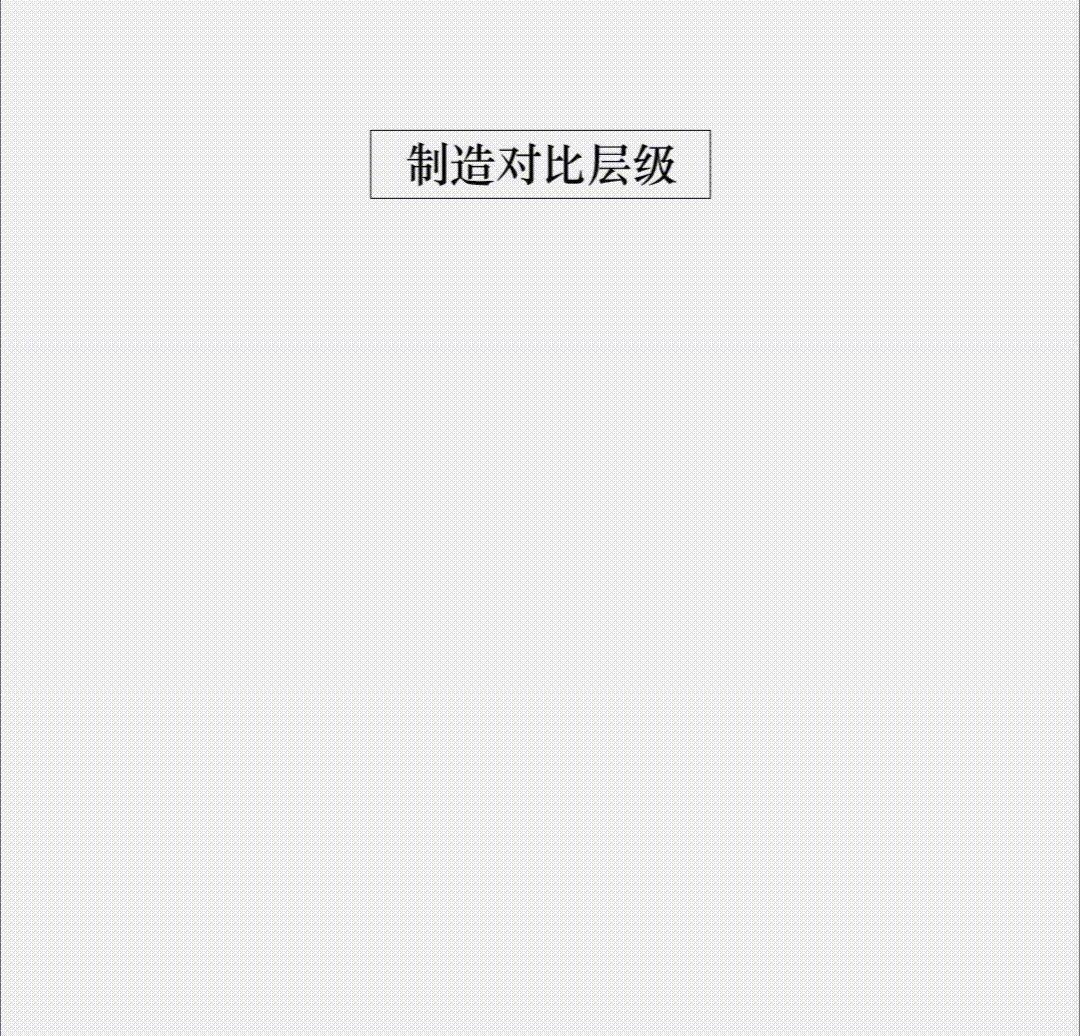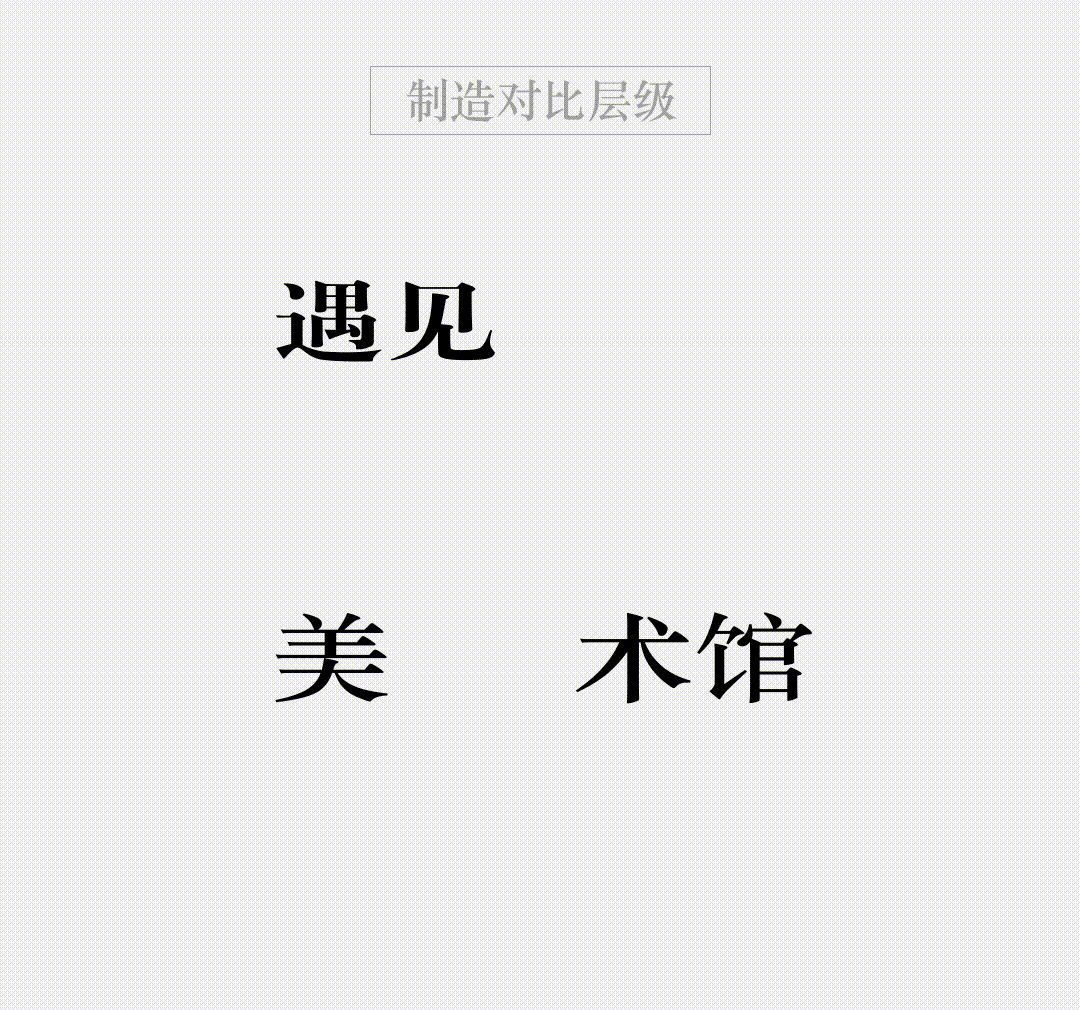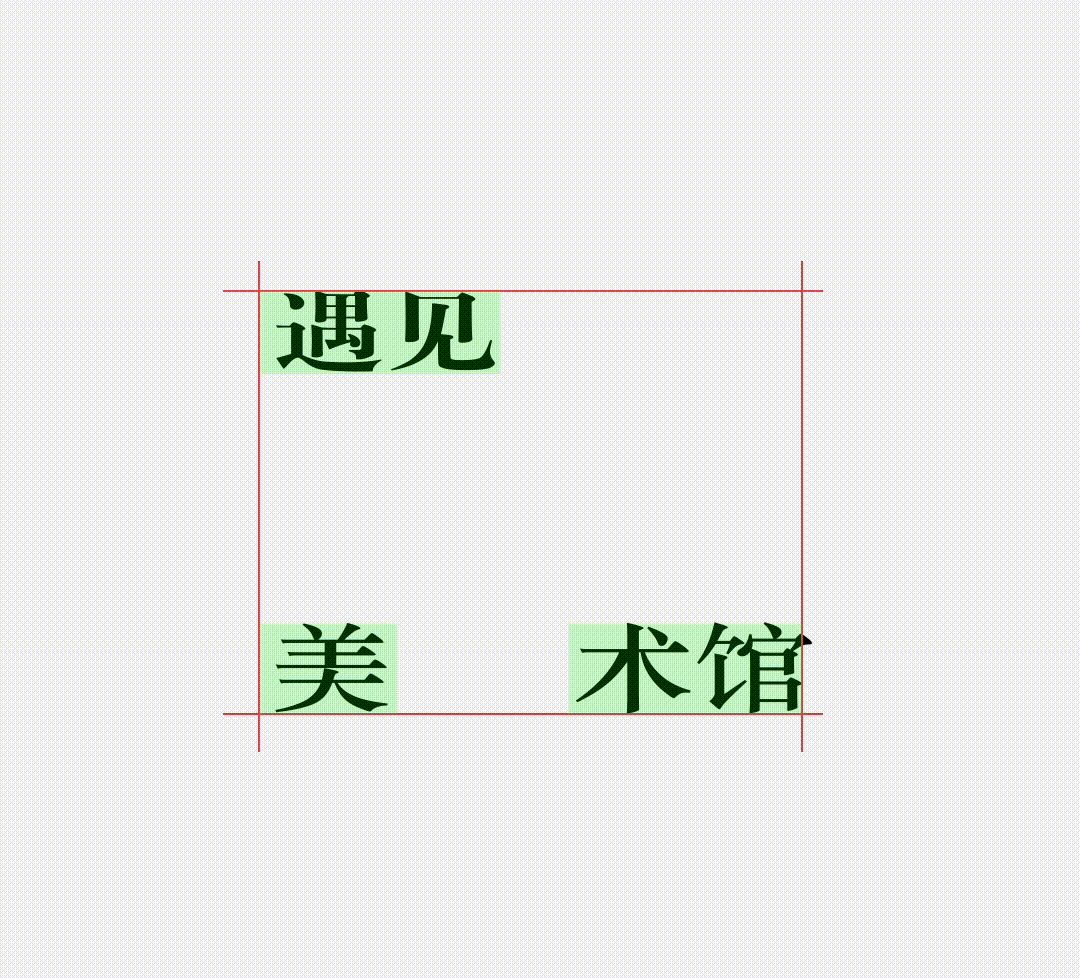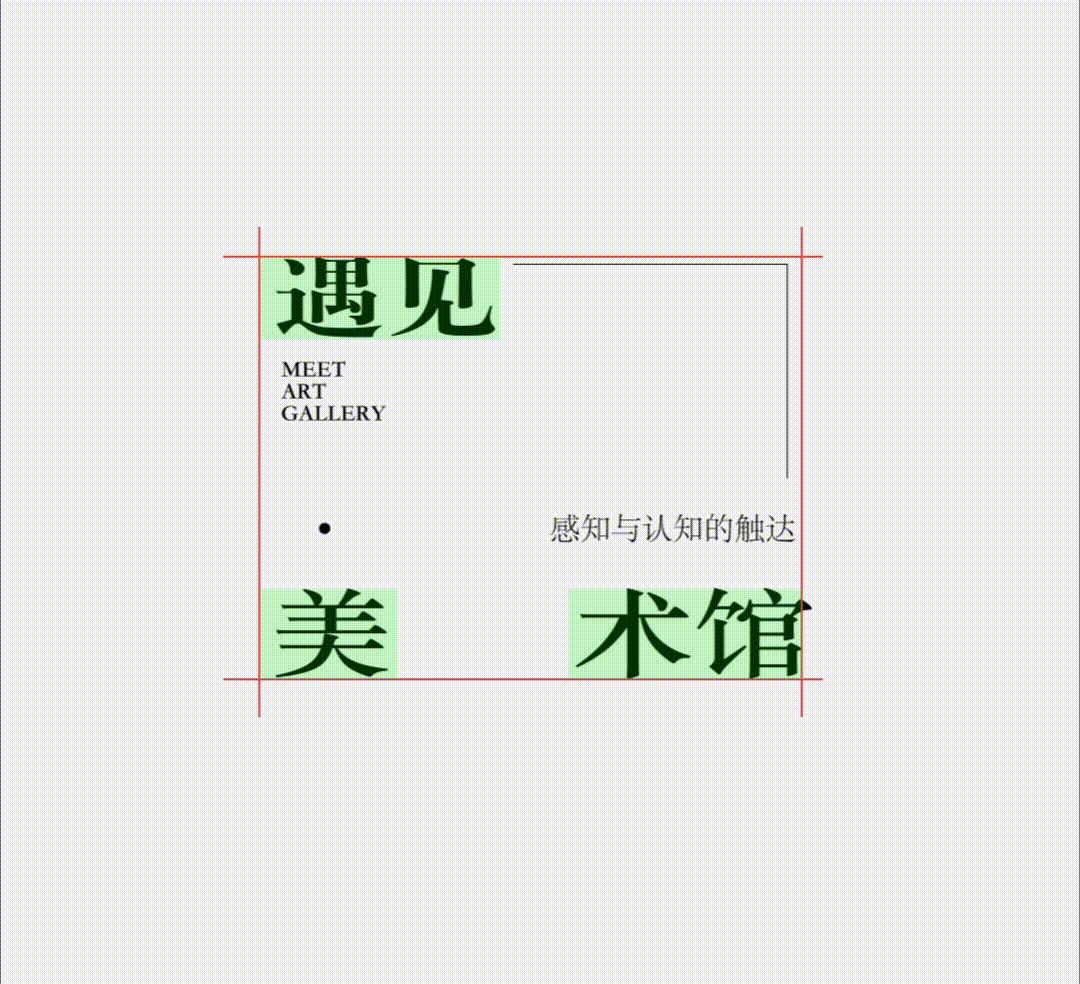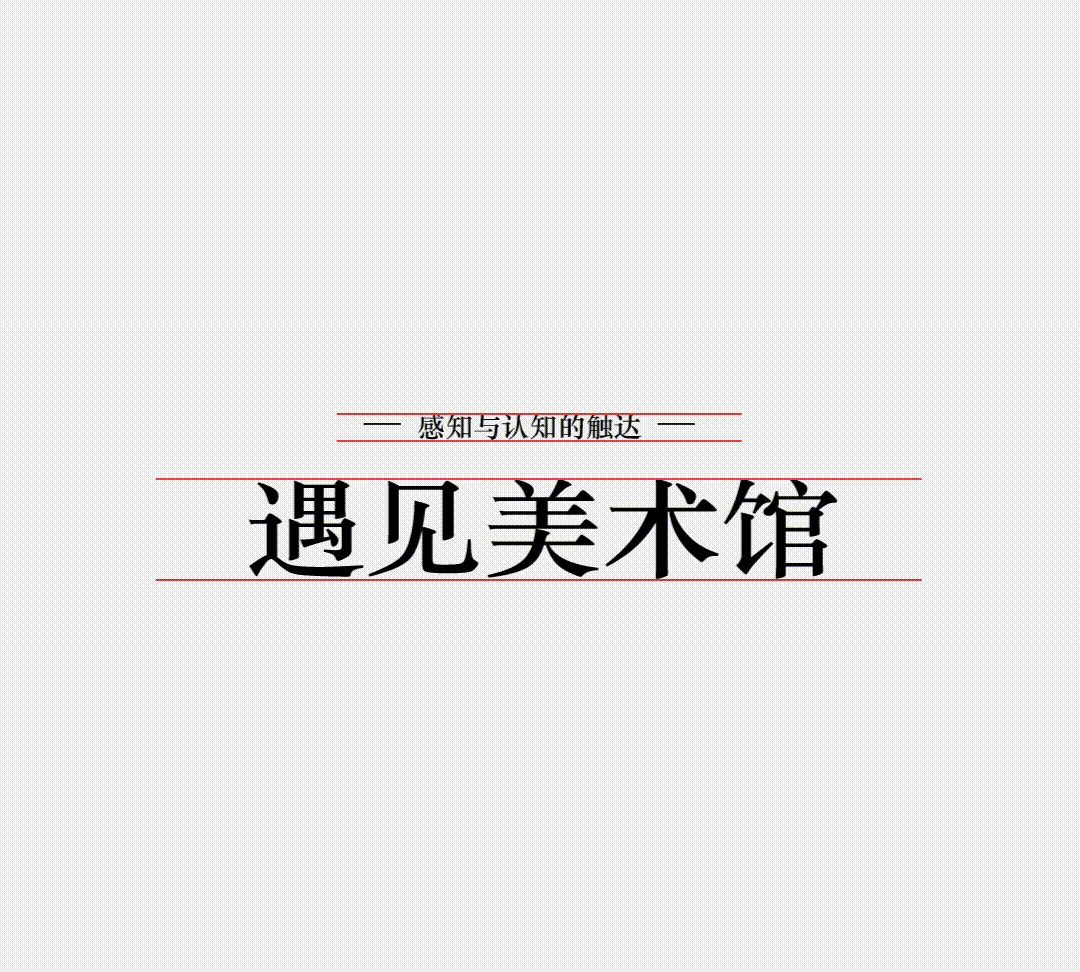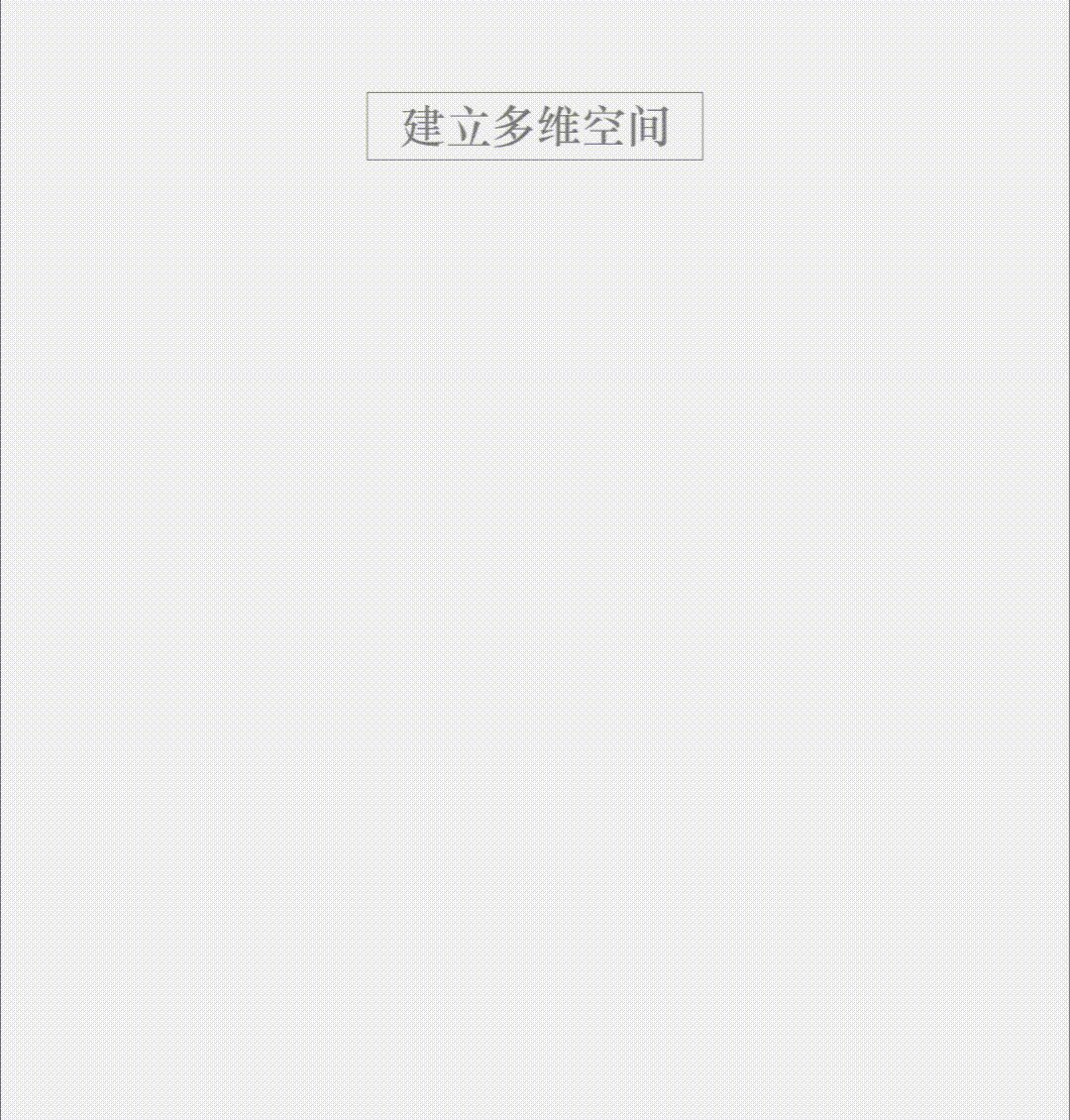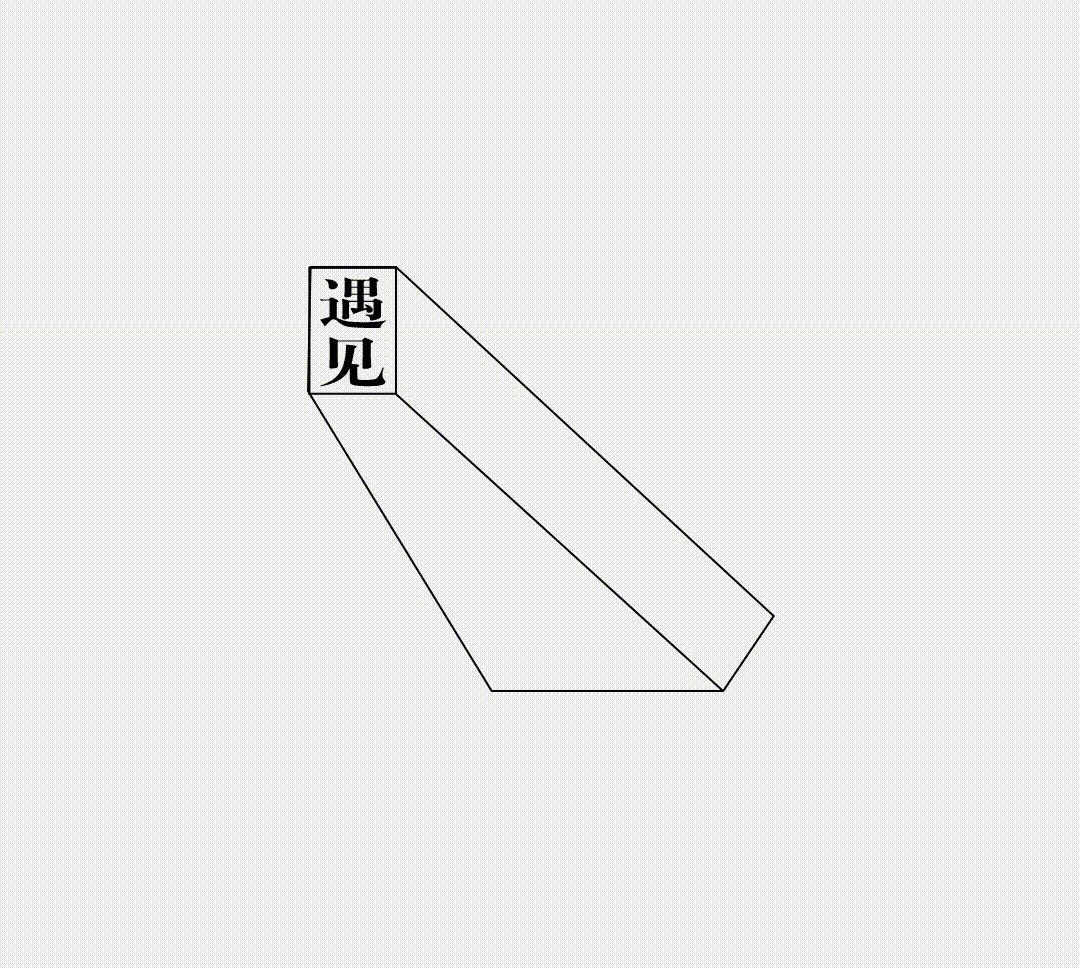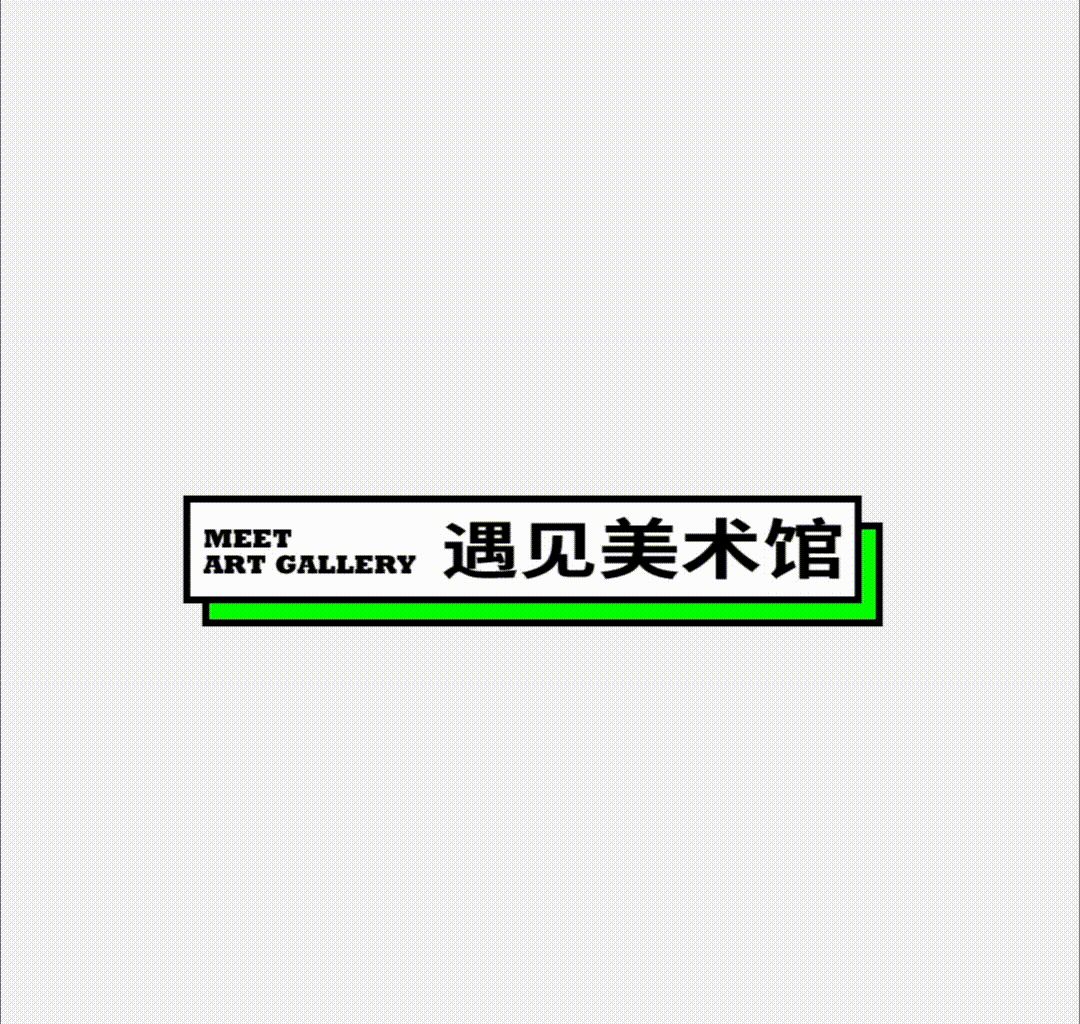
标题性文字怎么设计?
今天我们讲标题性文字怎么设计
常规的文字对齐放置,就像两个平行世界的人,永远无法相交,文字的对齐与相等间距,其看上去的规整秩序也只是职场中的表面和善一样,缺少了信息的真实表达。
将遇见与美术馆进行了分层方式,就像表白说出口的我爱你,总要用断句的方式,我,爱你来的更加深情和真挚。
文字放置后形成四周的框架来约束画面的稳定,用杨蒙恩求婚时说的那句话再合适不过:这个世界上,没有天生的好人,只有被约束的文明者,框架的约束形成了稳定的秩序和美观性。
但情人总是分分合合,转了一圈,最终还是回到了框架之内,因为发现没有人比你更合适自己,内部的流动空间增加了信息和装饰解决了空间留白过多的问题。
再用一根线条callback回到主题,遇见美术馆,而美与术故意留出的空间,增加你们对艺术的遐想。
同样的文字,强弱的对比关系制造出了大小的层级。
用圆形围着四周形成了装饰性的设计元素制造律感。
而强弱对比所衍生出的三角构图帮助画面增加了上下的平衡稳定,这么多的设计小心思,告诉我们,约女生出门时,是需要等的。
还是同样的文字,遇见告诉我,它喜欢的人在另一个城市,但是手机的黄码却告诉它,原来都是时空伴随者。(一不小心在家隔离了,实惨!)
利用线塑造出的伪空间,提升了画面的立体感,让设计的表达变得更加多样化。
当用线在平面中塑造出了美术馆的立体空间后,文字的信息与图形很自然地融合在了一起,而文字告诉我,别人都不曾费心设计,别人都觉得思考太麻烦,所以没人发现过我的美丽,所以没人到过这里。
这次我们给文字外加个框,一个框太寒碜。
要想生活过得去,身上总得带点绿,再加一个绿色的框,两框重叠,这样CP就锁死了。
再放置一个大卫和他迷离的小眼神,结合传达出来的文字,仿佛在告诉我们,艺术就是装X。
装饰元素与黑边线框的组合搭配,便是带着枷锁到现在还在跳舞的我们。黑色线框与扁平化的元素图形让视觉变得更加直观且诙谐有趣。
综合以上三种标题设计方式,我们看到了利用小细节设计的标题,文字不只是一种信息,也只一种感受和情感的表达。